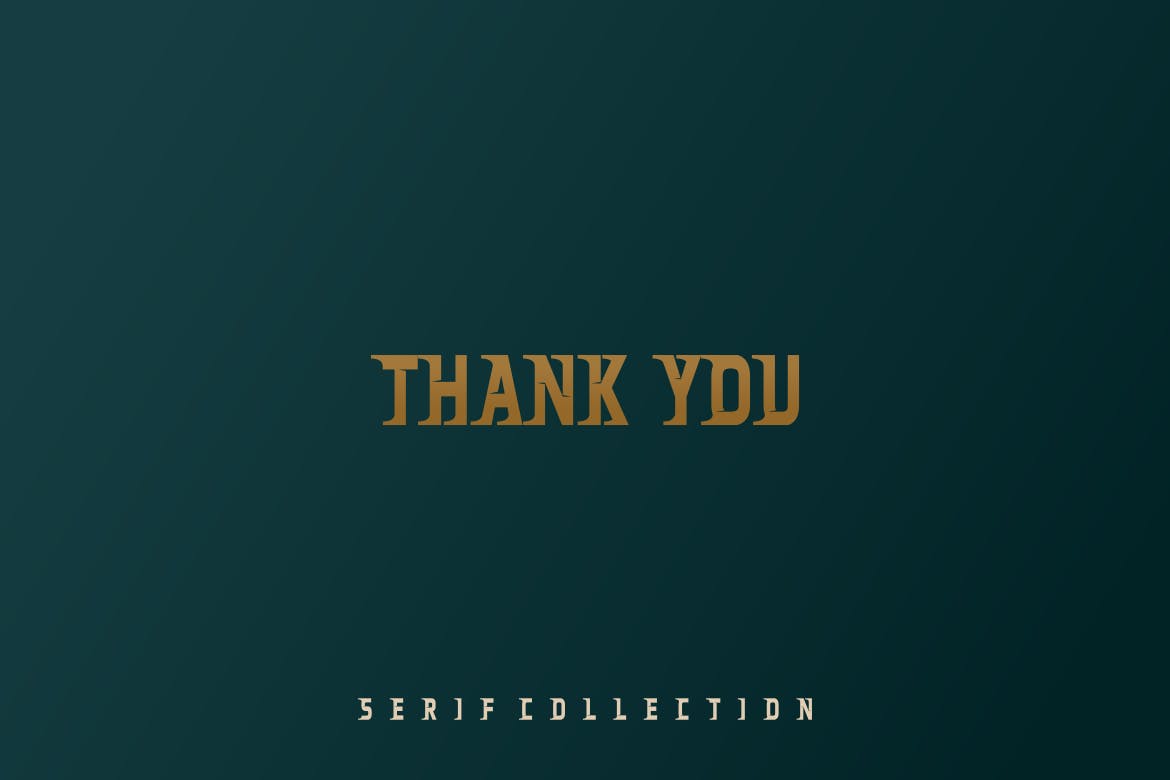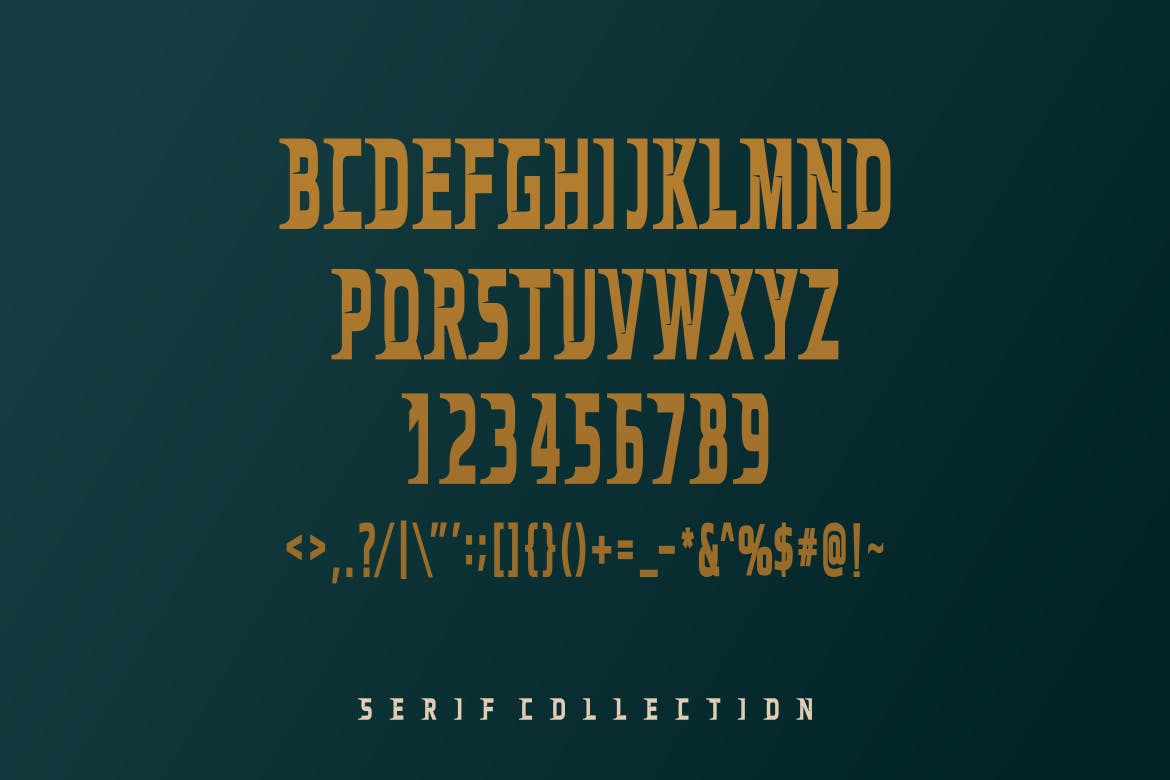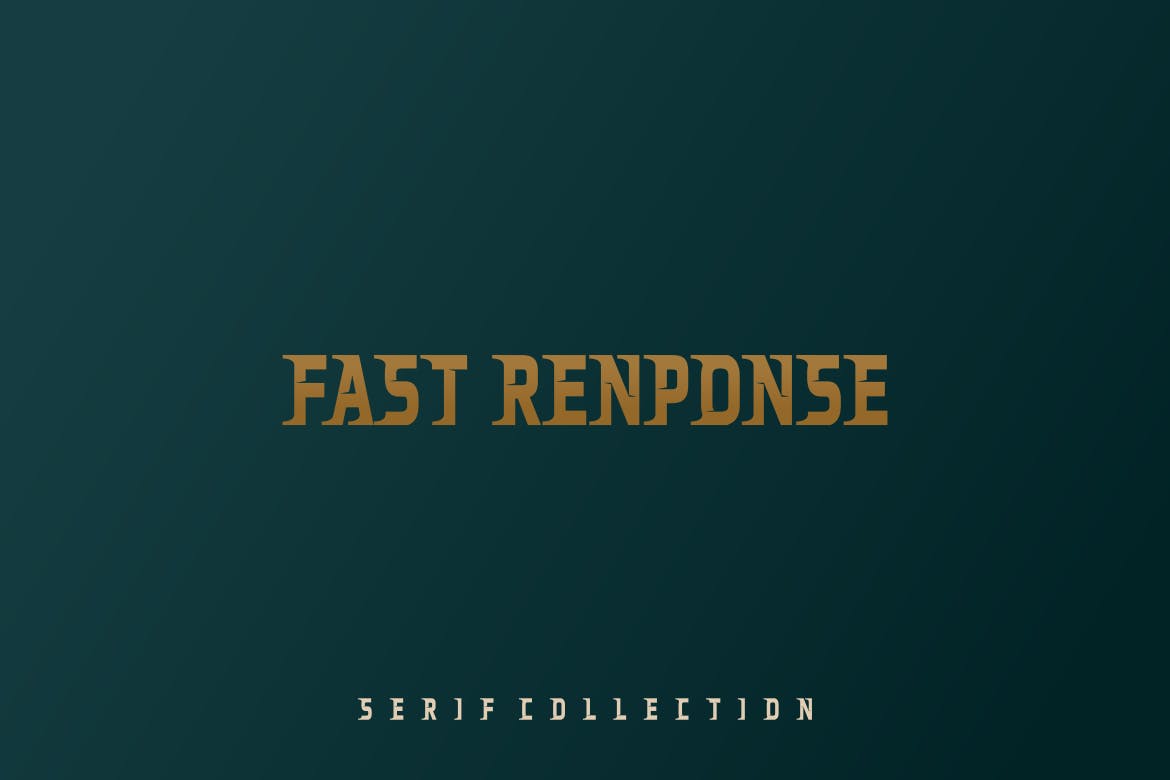
معرفی محصول جدید ما، فونت Fasticana - فونت مدرن.
فونت Fasticana - فونت مدرن، یک فونت نمایشی جسور و اصیل است. این فونت برای هر پروژه برندینگ مانند طراحی لوگو، چاپ تیشرت، ورزشهای الکترونیکی و بسیاری دیگر مناسب است و در انواع مختلف زمینهها برجسته است.